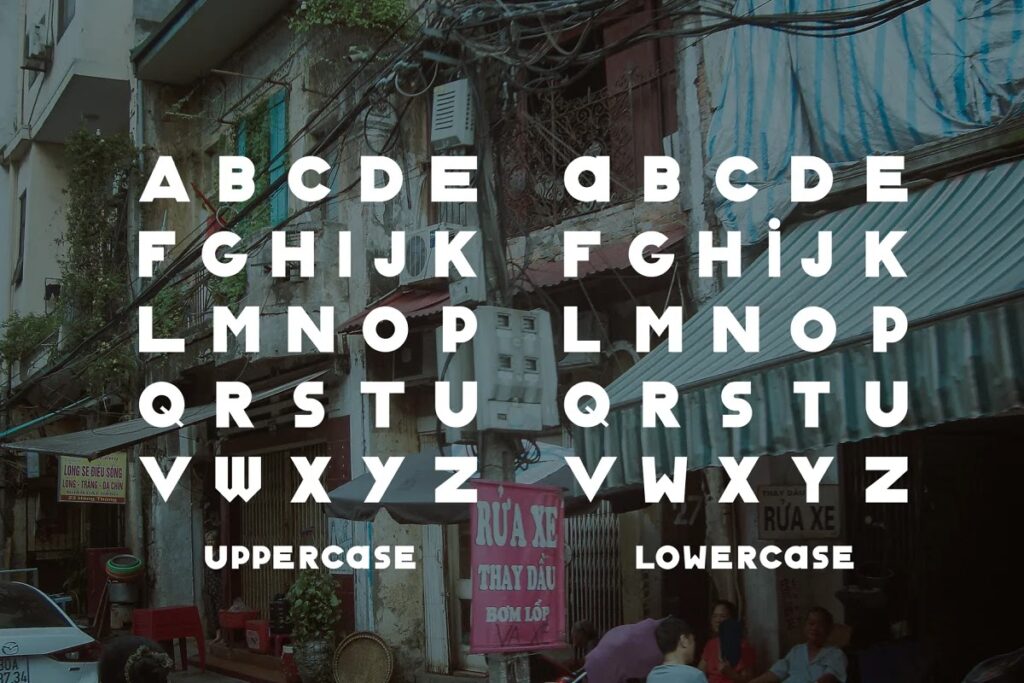
Nhiều designer khi tải font retro thường gặp tình trạng font đẹp nhưng không có dấu tiếng Việt, thiếu ký tự hoặc hiển thị không đúng khi đưa vào thiết kế. Điều này khiến bố cục bị sai lệch và mất nhiều thời gian tìm font thay thế. Ở bài viết này, Xưởng In Viva sẽ cung cấp link download Classique Saigon font việt hóa miễn phí và cách sử dụng phù hợp.
Trước khi sử dụng một font chữ trong dự án thiết kế, việc hiểu rõ bản chất của font sẽ giúp bạn chọn đúng kiểu chữ cho đúng bối cảnh. Với những font thuộc nhóm retro như Classique Saigon, yếu tố hình dáng chữ, cảm giác thị giác và mức độ gợi nhớ bối cảnh xưa cũ là điều rất quan trọng.
Classique Saigon Typeface là một kiểu chữ mang tinh thần hoài cổ, được xây dựng dựa trên cảm hứng từ bảng hiệu, poster và các hình thức quảng cáo thị giác từng xuất hiện tại Sài Gòn vào những thập niên trước. Đây là nhóm font đặc biệt phù hợp với các thiết kế cần màu sắc vintage, bản địa và có cá tính rõ ràng.
| Tên font | Classique Saigon |
| Kiểu chữ | Display / Retro |
| Phong cách | Vintage Sài Gòn |
| Ứng dụng | Poster, logo, bảng hiệu |
Classique Saigon Typeface là gì?
Classique Saigon Typeface là một font chữ display mang tinh thần retro, được lấy cảm hứng từ ngôn ngữ thị giác của Sài Gòn giai đoạn khoảng thập niên 60–80. Đây là thời kỳ mà bảng hiệu, poster quảng cáo và các biển tiệm thường có phong cách chữ rất riêng: đậm, nổi, giàu tính trang trí nhưng vẫn gần gũi và dễ nhận diện.
Khác với các font sans-serif hiện đại thiên về sự tối giản, classique saigon font việt hóa được tạo ra để gợi cảm giác ký ức, đô thị cũ và vẻ đẹp thị giác của một Sài Gòn nhiều lớp văn hóa. Khi đặt vào đúng bố cục, font này không chỉ hiển thị chữ mà còn góp phần tạo ra bầu không khí cho toàn bộ thiết kế.
Đó cũng là lý do nhiều người tìm font classique saigon việt hóa để dùng trong các dự án branding, poster, menu quán cà phê hoặc các sản phẩm thiết kế cần chất retro rõ nét.
05 đặc điểm nổi bật của Classique Saigon Font
Điểm mạnh của Classique Saigon không nằm ở sự trung tính mà nằm ở bản sắc thị giác rất rõ. Đây là kiểu font dễ tạo ấn tượng và có thể thay đổi hoàn toàn tinh thần của bố cục chỉ bằng một dòng tiêu đề.
Dưới đây là những đặc điểm nổi bật khiến nhiều designer lựa chọn classique saigon typeface cho các dự án sáng tạo:
- Nét chữ retro rõ rệt: font gợi nhớ ngay đến biển hiệu và poster của Sài Gòn xưa, tạo cảm giác hoài cổ rất đặc trưng.
- Đường nét đậm và chắc: giúp phần tiêu đề nổi bật hơn, đặc biệt hiệu quả khi dùng ở kích thước lớn.
- Phong cách vintage có cá tính: không đơn thuần là “cũ”, mà mang chất thị giác riêng phù hợp với các dự án cần kể câu chuyện thương hiệu.
- Dễ tạo điểm nhấn trong bố cục: chỉ cần dùng cho một cụm từ ngắn hoặc logo là đã có thể tạo ấn tượng mạnh.
- Phù hợp branding retro: đặc biệt thích hợp với quán cà phê, nhà hàng, sản phẩm thủ công hoặc thương hiệu cần chất hoài niệm.
Nhờ những đặc điểm này, classique saigon font việt hóa thường được xem là một lựa chọn giàu cảm xúc hơn so với nhiều font display phổ thông.
Ứng dụng của Classique Saigon Font trong thiết kế
Classique Saigon không phải là kiểu chữ dành cho mọi loại dự án, nhưng nếu dùng đúng bối cảnh, font này có thể tạo ra hiệu quả thị giác rất mạnh. Đây là nhóm font phù hợp với những thiết kế cần bản sắc, cần chất hoài cổ hoặc muốn gợi nhớ đến tinh thần Sài Gòn xưa theo cách hiện đại hơn.
Một số ứng dụng phổ biến khi tải font classique saigon gồm:
- Poster retro hoặc poster quảng cáo phong cách xưa.
- Logo quán cà phê, tiệm ăn, cửa hàng mang concept hoài niệm.
- Thiết kế bảng hiệu hoặc menu mang cảm hứng vintage.
- Branding retro cho sản phẩm hoặc dự án sáng tạo.
- Poster quảng bá sự kiện theo concept Sài Gòn cũ.
- Thiết kế bao bì sản phẩm cần sự khác biệt và cảm xúc bản địa.
Nhờ phong cách thị giác độc đáo, classique saigon font việt hóa giúp thiết kế không chỉ đẹp hơn mà còn dễ ghi nhớ hơn trong mắt người xem.
Classique saigon font việt hóa là lựa chọn phù hợp cho những thiết kế muốn tái hiện không khí Sài Gòn xưa theo một cách vừa hoài niệm vừa có tính ứng dụng. Khi dùng đúng classique saigon typeface, bạn có thể tạo ra các thiết kế giàu cảm xúc, có bản sắc rõ ràng và dễ ghi nhớ hơn.